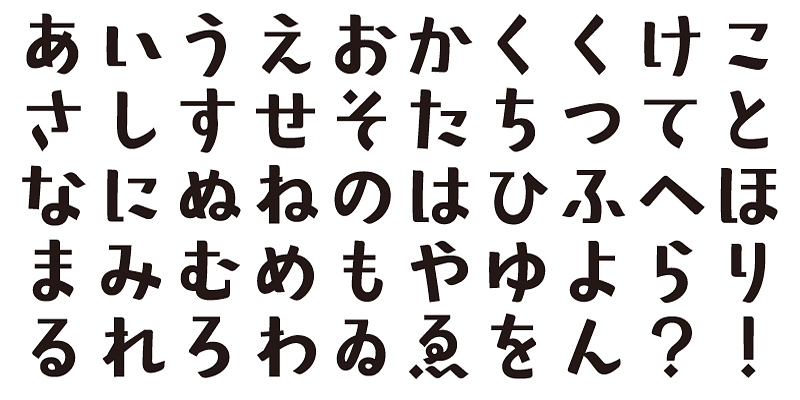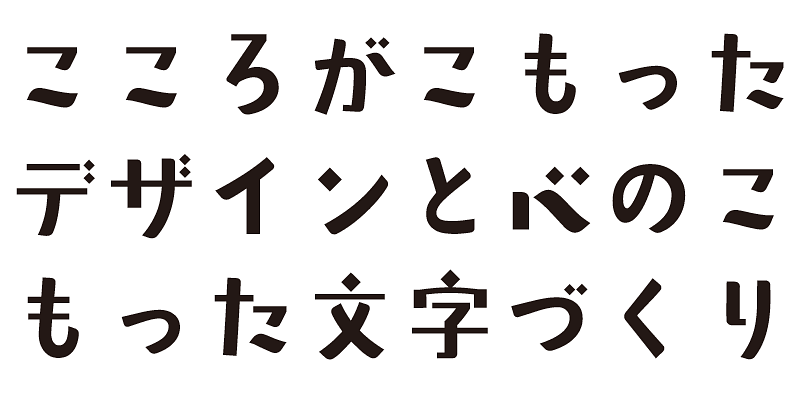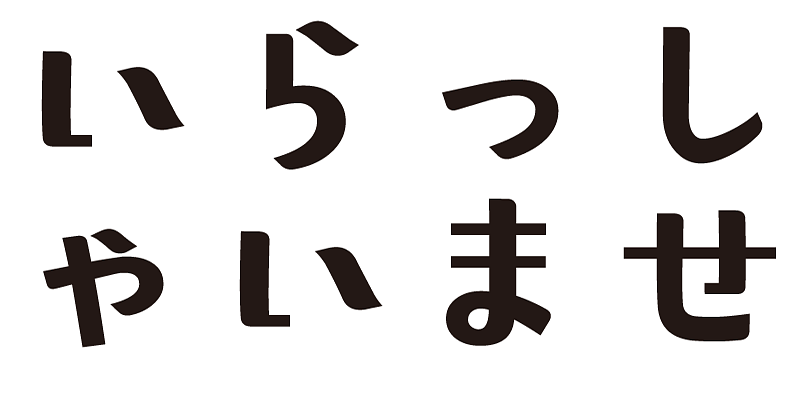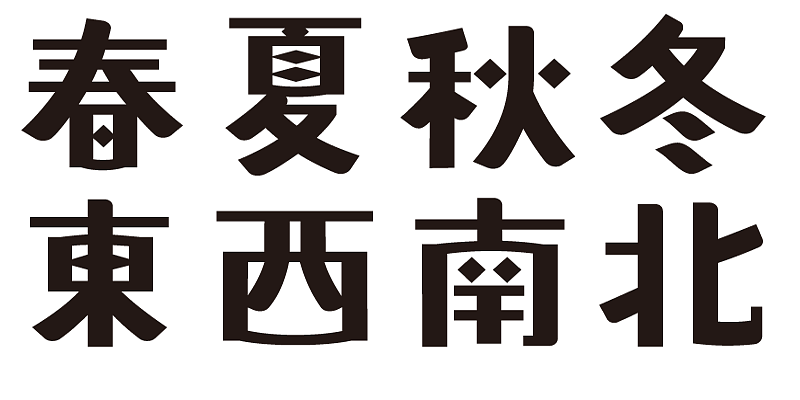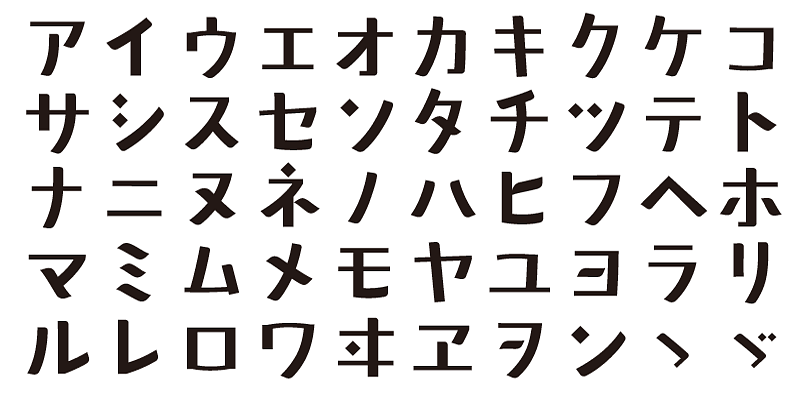
Une police de style moderne avec une touche rétro.
Chaque police de cette famille de polices comprend 1 000 caractères kanji, ainsi que des caractères hiragana, katakana, alphanumériques et des signes de ponctuation.
Nous concevons des polices dans l’espoir qu’elles ajouteront une signification sous-jacente aux mots exprimés. Nous souhaitons que l’utilisateur se sente bien et qu’il éprouve du confort et de la joie lorsqu’il utilise ces polices.